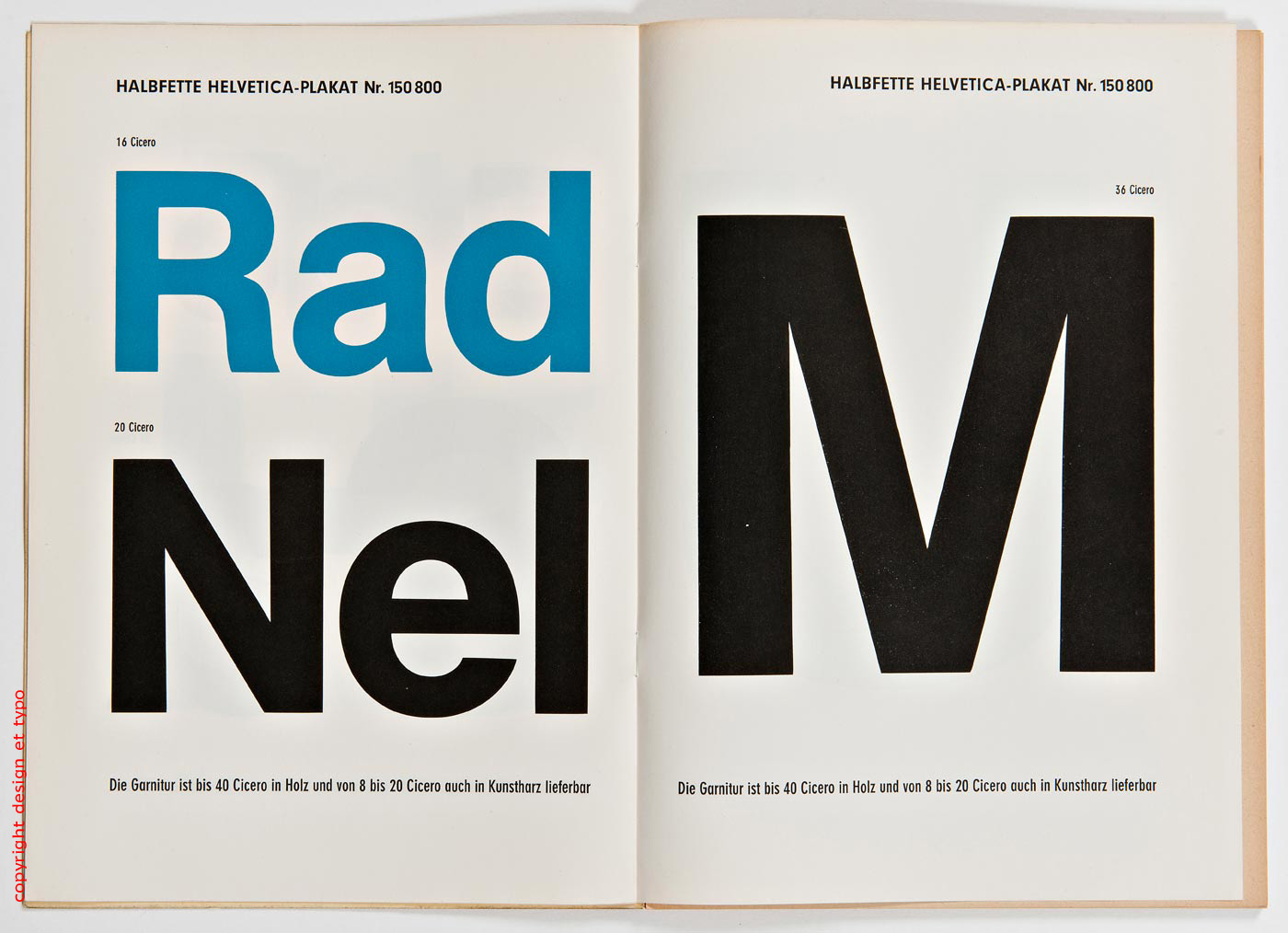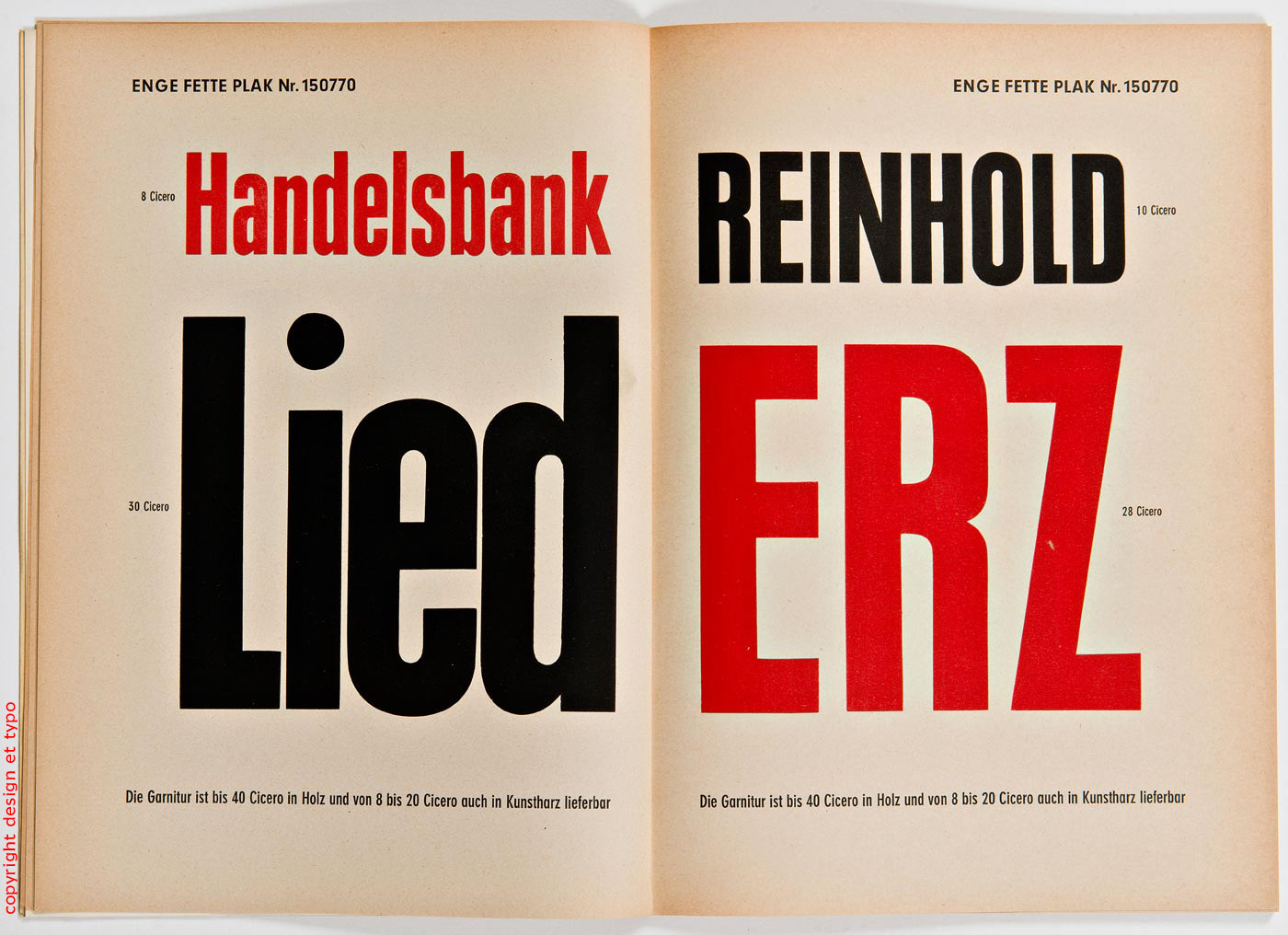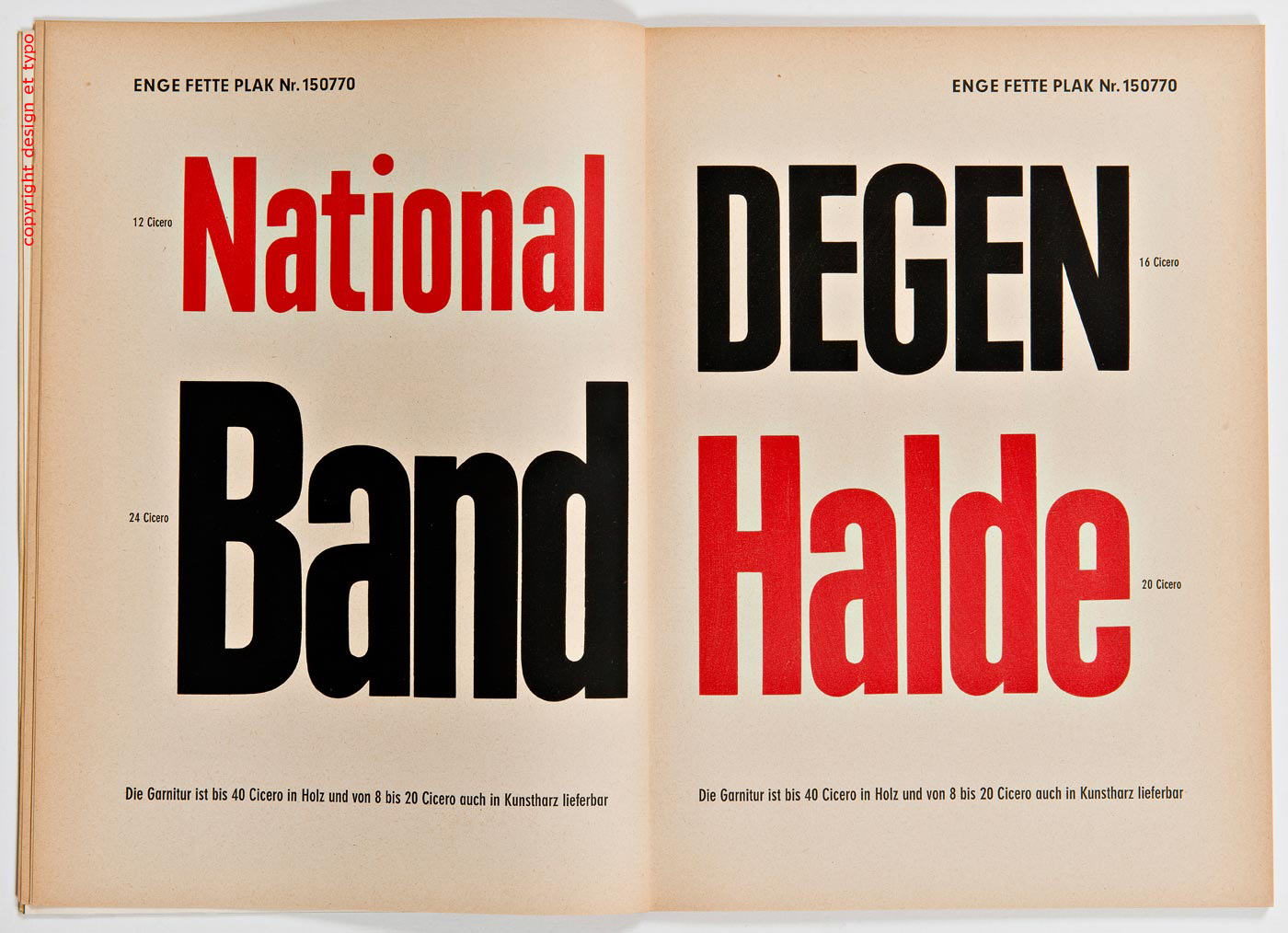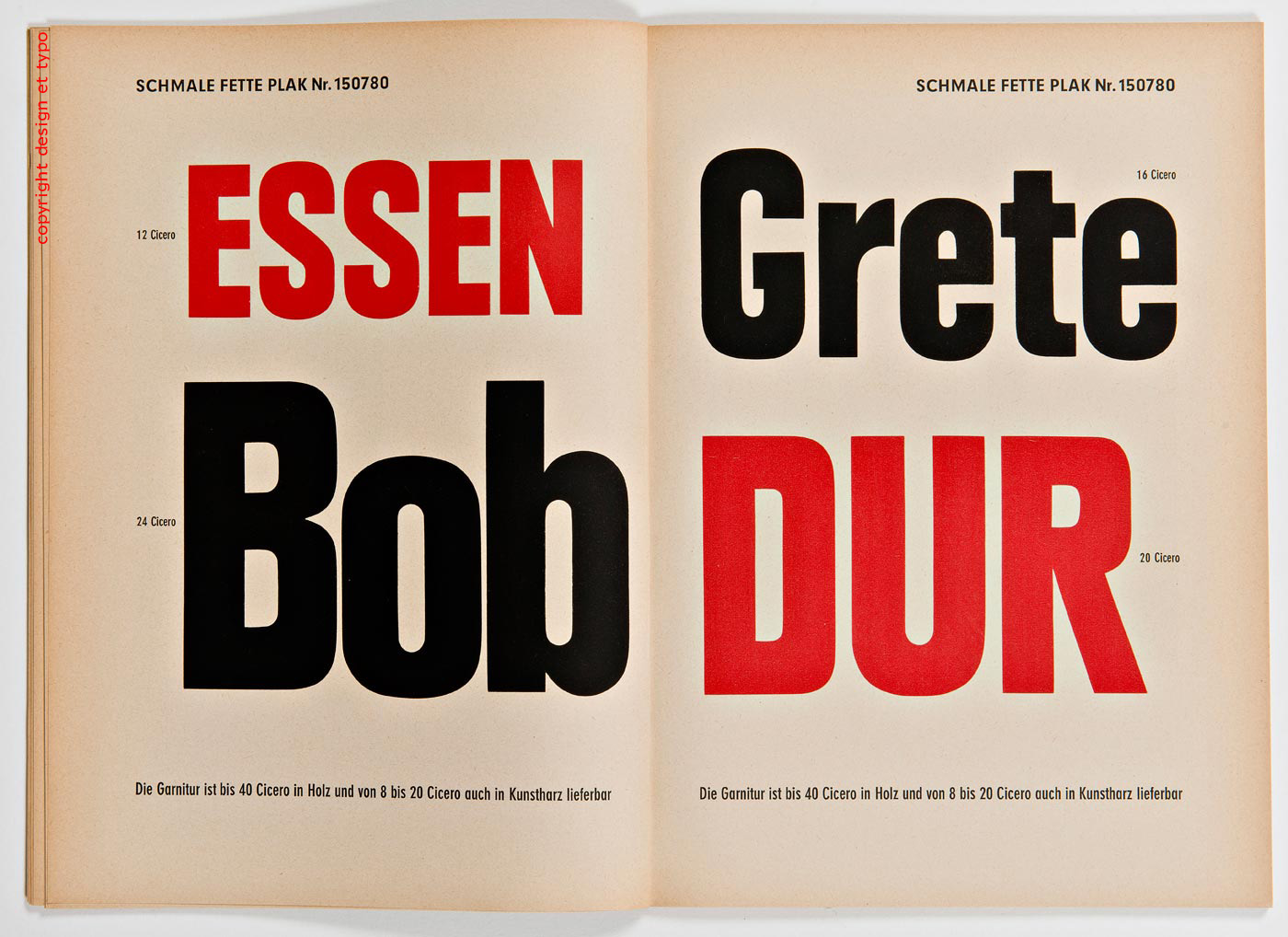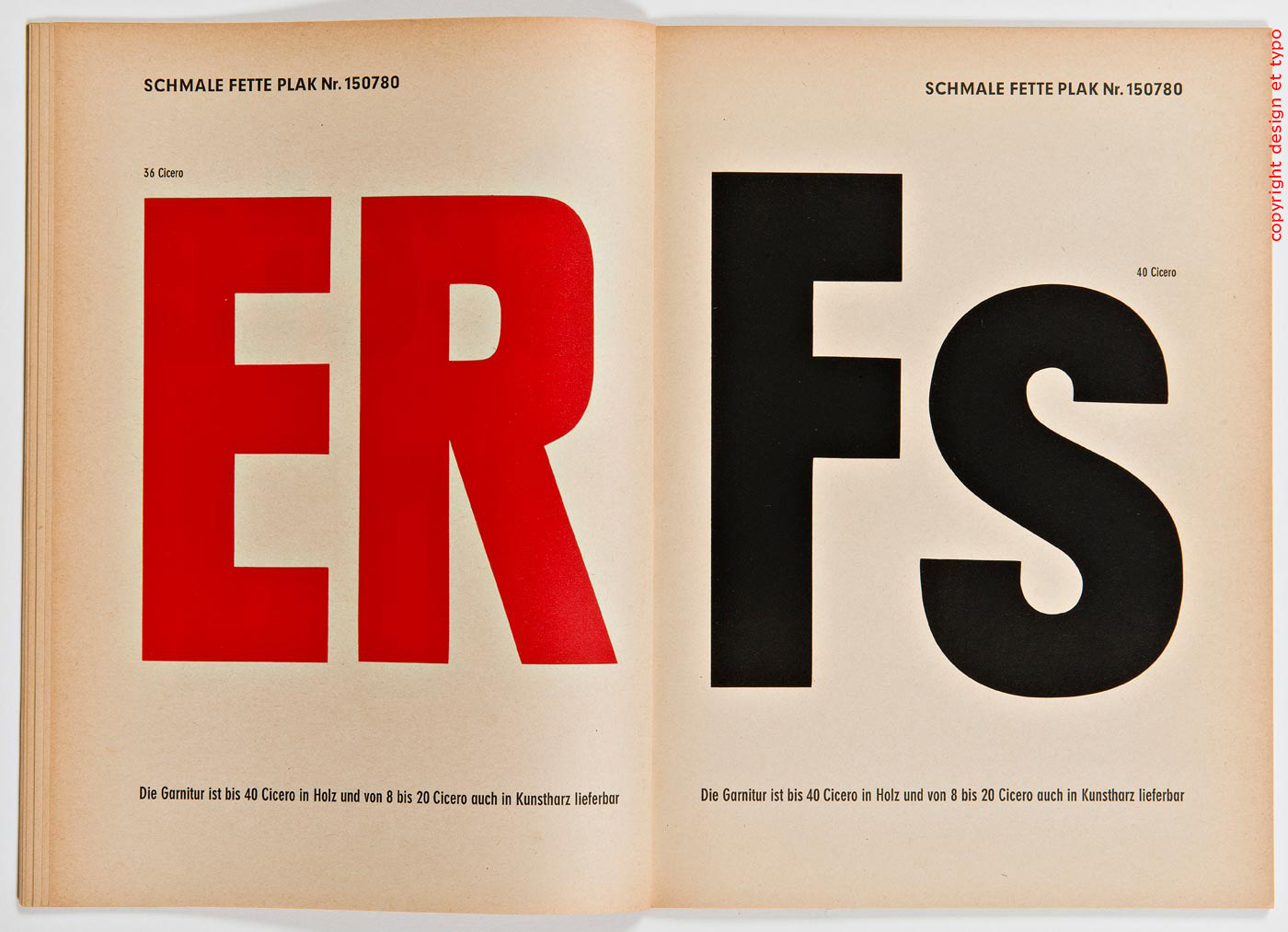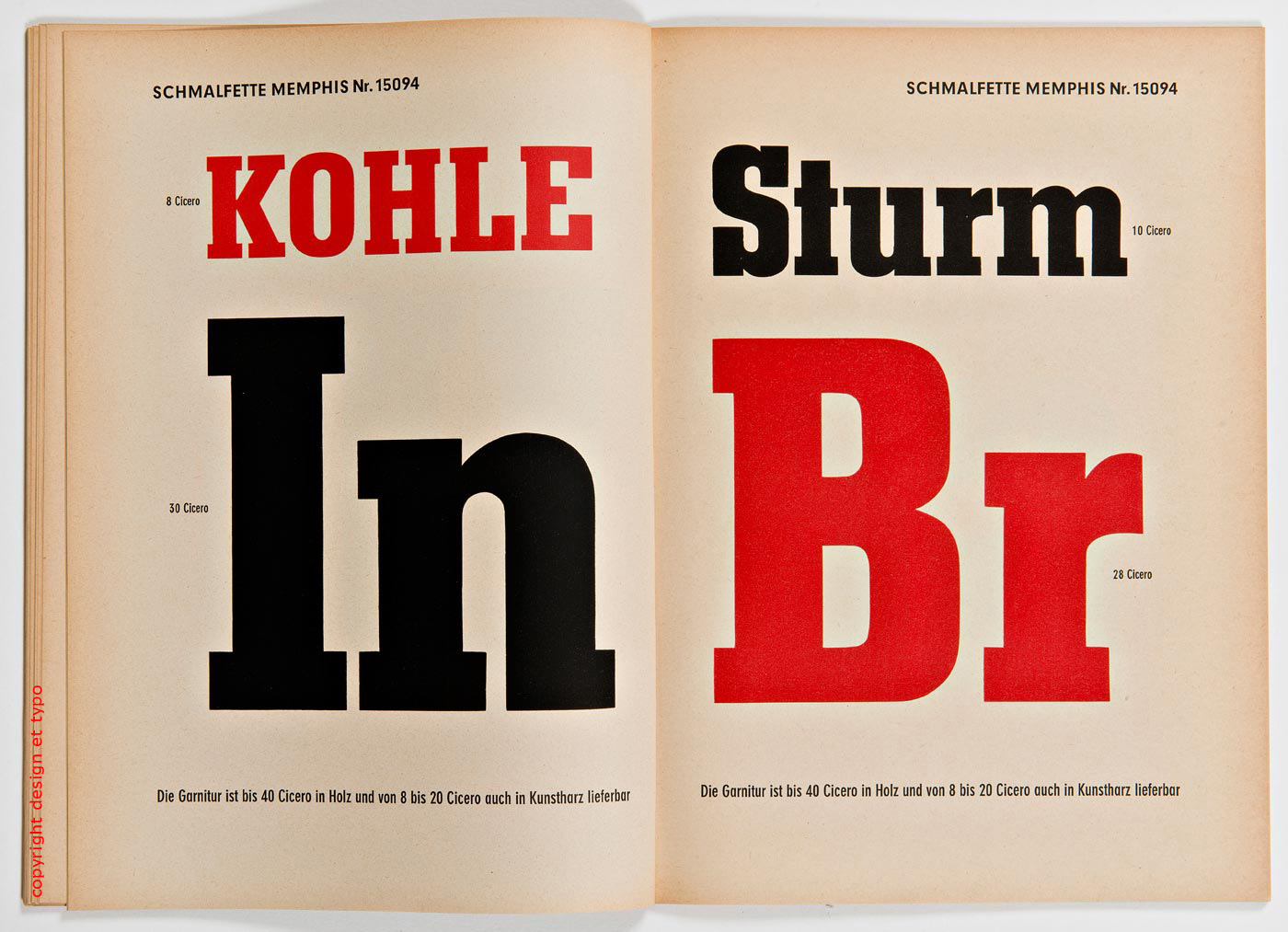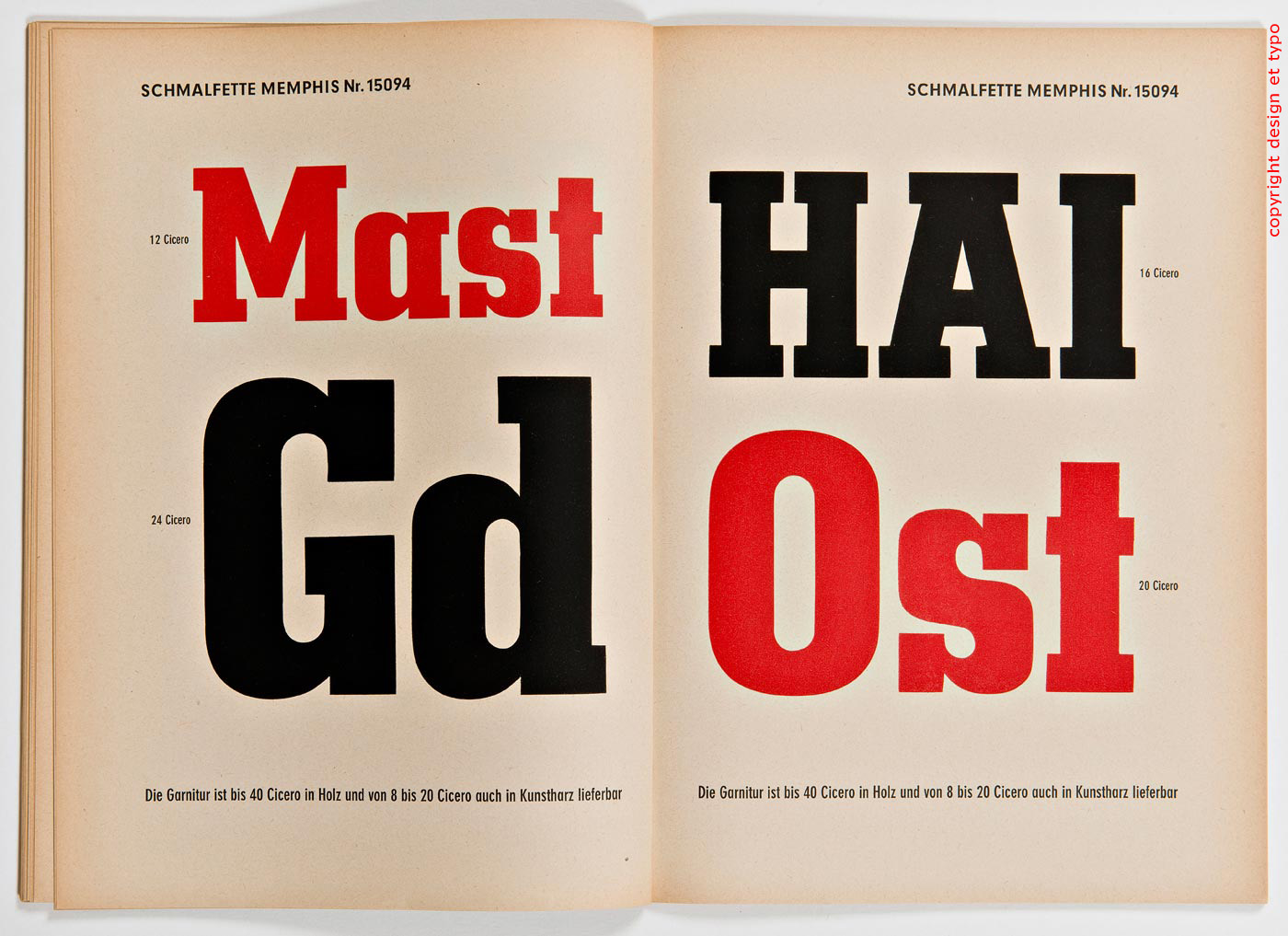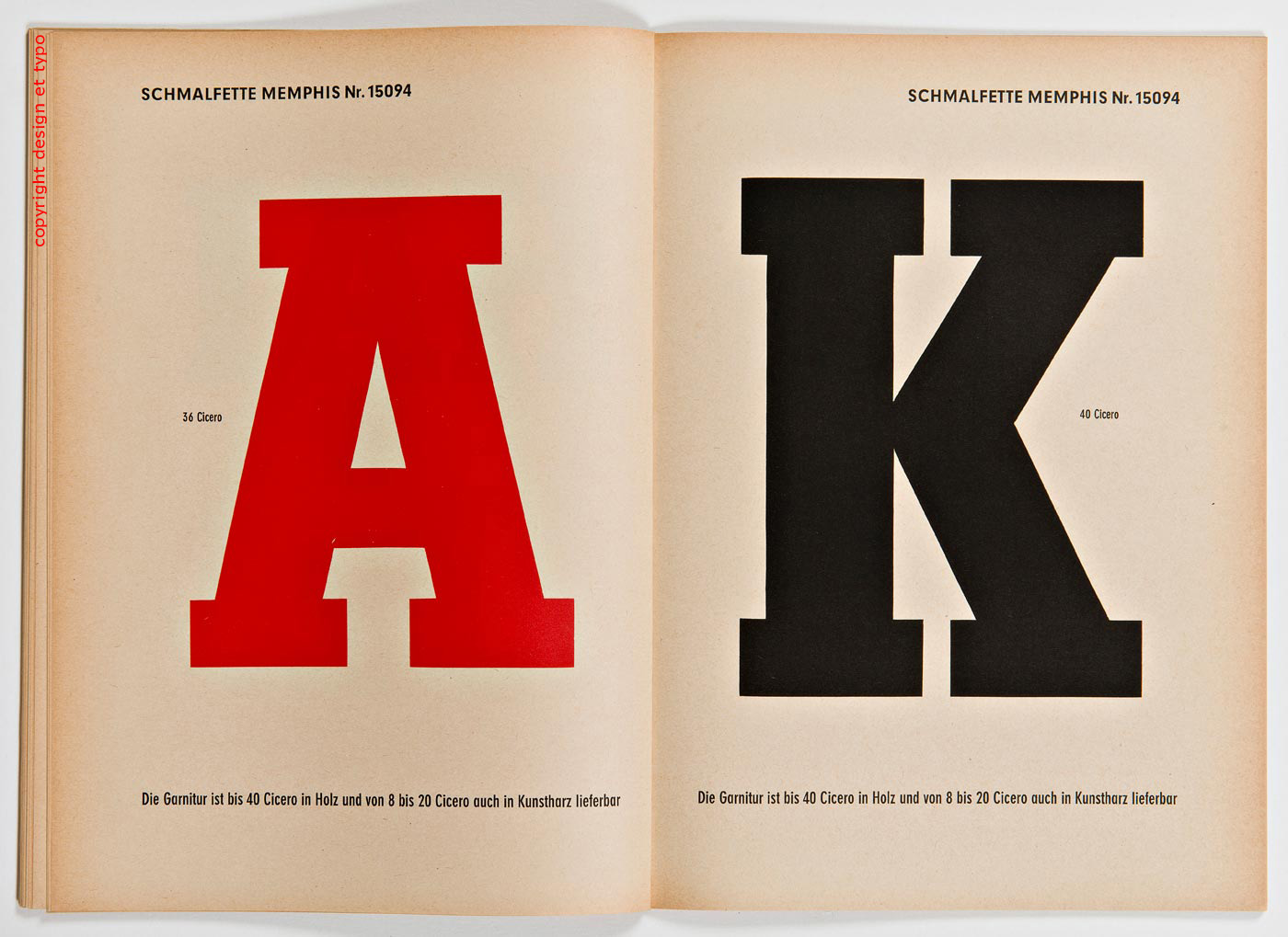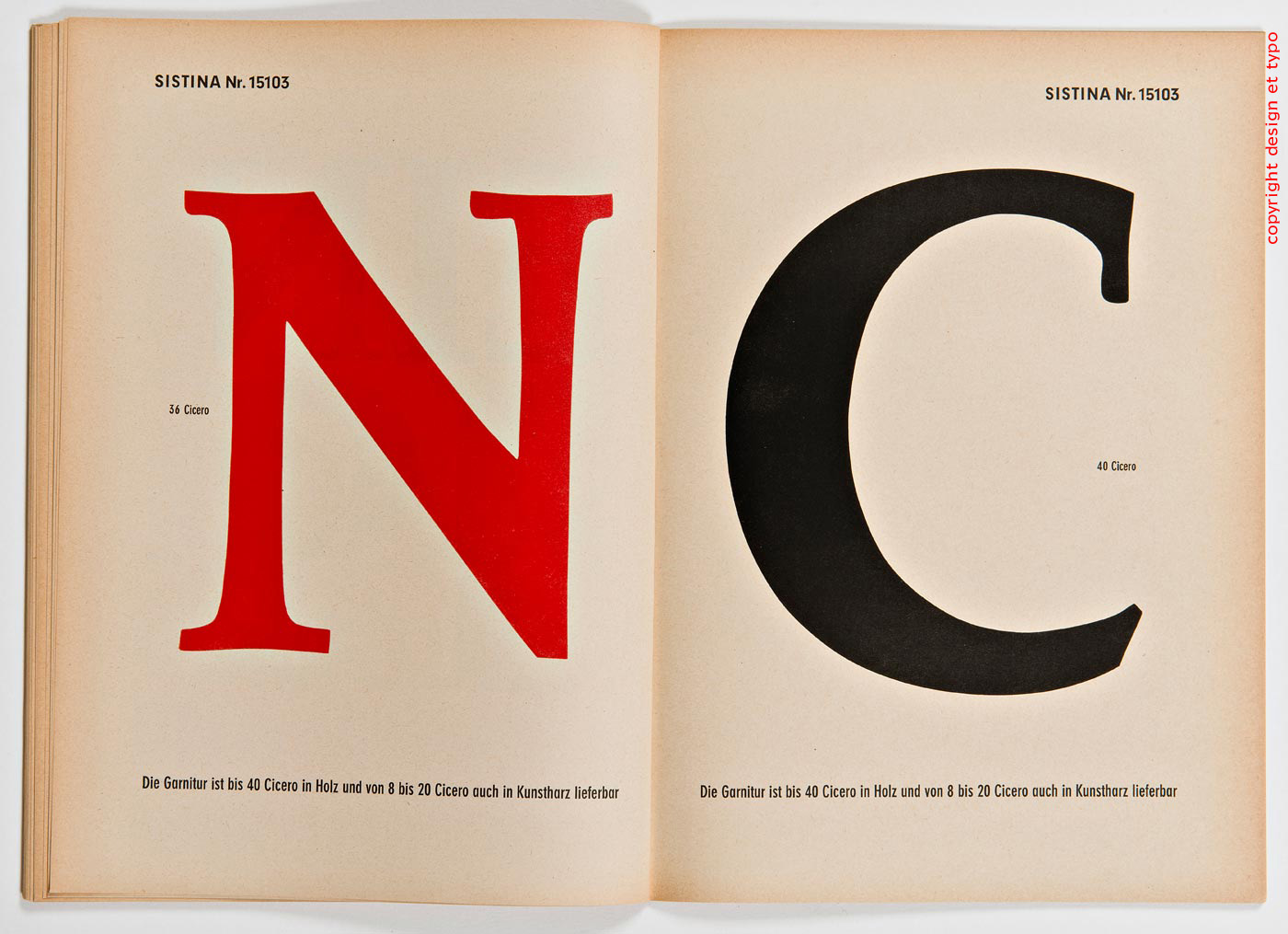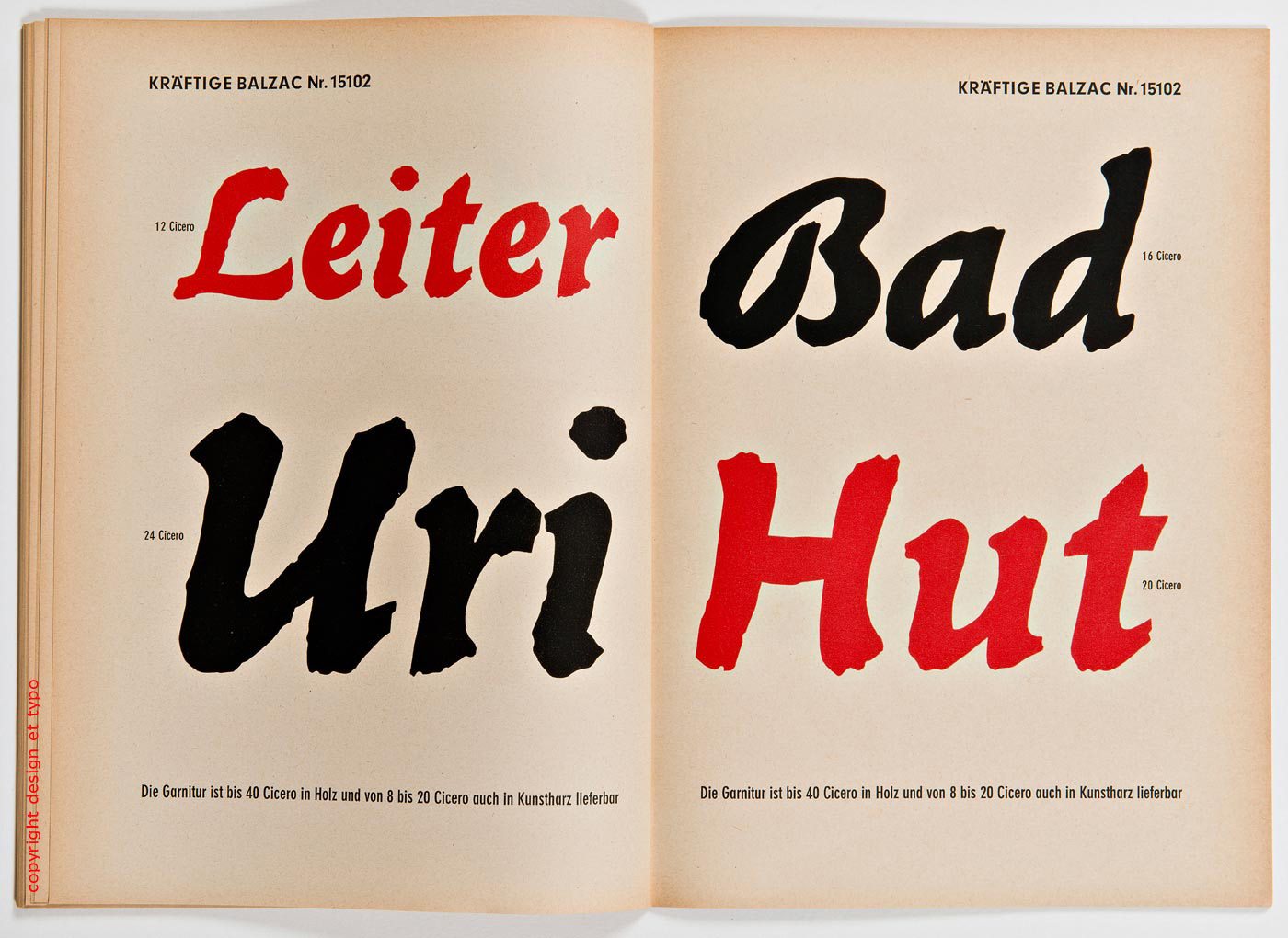
Fonderie Stempel | Caractères de Titrage | Plakat Schriften
Littéralement «Écritures d’Affiche» Stempel qui de l’autre côté du Rhin constituait l’un des fleurons de la typographie traditionnelle (rachetée depuis par Linotype puis par Montotype) éditait de même que Deberny et Peignot ou la Fonderie Olive en France (qui étaient à proprement parler de tailles minuscules comparées à leurs collègues germaniques) des plaquettes de spécimen de caractères pour le même usage que je décrivais précédemment pour les spécimens de Deberny et Peignot.
Ah j’oubliais, la date? nous sommes sans doute dans les années 50, et la mise en page devait être supervisée par Hermann Zapf lui-même, puisque celui-ci était le directeur artistique de Stempel durant de longues années.
Caractère de titrage l’Helvetica Bold
ou le Enge Fette Plak
ou encore le Schmale fette Plak
et bien sûr le Fette Plak
Mais on va aussi trouver une mécane, le Memphis Bold ou Schmalfette Memphis
Puis on passe au Sistina, Garalde dérivée du plus pur Garamond
et l’on va terminer par le Script Balzac et…
l’Elan demi-gras, rien à voir avec l’Elan d’Alber Boton
Ici le Ziffern, police pour des chiffres de titrage